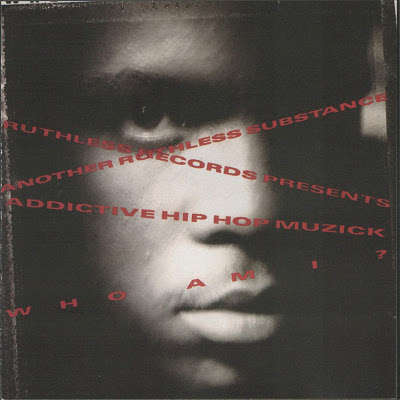
Ich hatte diese Idee von einem Thread in dem typografische Kapitalverbrechen gepostet werden können als ich mir ein paar alte HipHop CD Covers von den frühen 90'er anschaute und sagen musste, uff, hat das nun ein Amateur gemacht oder war das der Stil von dieser Zeit?
Hier mal ein paar Beispiele:
Solche flippigen Schriften wie bei diesem Cover finde ich auch schrecklich. War sowas in den 80'er-90'er typografisch wirklich anerkannt? Kann ich mir nicht vorstellen.
Für solche Fälle gibt es schon ein Kategorie: Typo-Sünden dürben im Wiki. »Another Ruthless Substance« finde ich durchaus gelungen. Vielleicht ein Beispiel für die Ausnahme von der Regel zum Schriftendehnen und -sperren. :wink: Bei Cool Daddy ist zuminest die Illustration gut.
Sehr passend zum argsam aufgekotzten Ludenschlitten ist doch auch die Typo hier stimmig inszeniert?
Nö, das war glaub nicht das der Stil der Zeit war. Die kleinen Hip-Hop-Labels haben das einfach selber gemacht. Und die Leute hatten einfach keune Ahnung.
Einem Kumpel, der vor relativ kurzer Zeit in Dt. CDs in Eigenauflage rausgebracht hat, hab ich auch einfach mal machen lassen. Die haben ein ganz ähnlich, dreckigen Look gekriegt.
Und wenn es doch Absicht ist, um sich von den gestylten Labels auf Teufel komm raus abzusetzen?
Das kann man ja auch typografisch korrekt machen :?
patrick, ich kann dir aus erfahrung ein rat geben – schaue dir bitte nur gute sachen an und lass die schlechten einfach liegen.
du kannst die welt nicht verändern, seit dem es dtp für jeden gibt ist es doch logisch, dass es viele schlechte sachen gibt, woher sollen es alle so genau wissen?
ich habe mich vor vielen jahren über viele sachen aufgeregt, es hat aber nichts gebracht, ausser ein paar graue haare mehr.
seit langem habe ich mein auge für die guten sachen trainiert, es gibt viel davon.
Das sehe ich ein wenig anders. Ich bin im Moment noch ein ziemlicher Dillettant was die Anordnung mit der Schrift angeht. Z.B. empfinde ich ein paar der Layouts als ziemlich geil obwohl die ja eigentlich nicht gut sind :P
Somit kann man schon profitieren wenn man sich Beispiele nimmt wie man es nicht machen sollte.